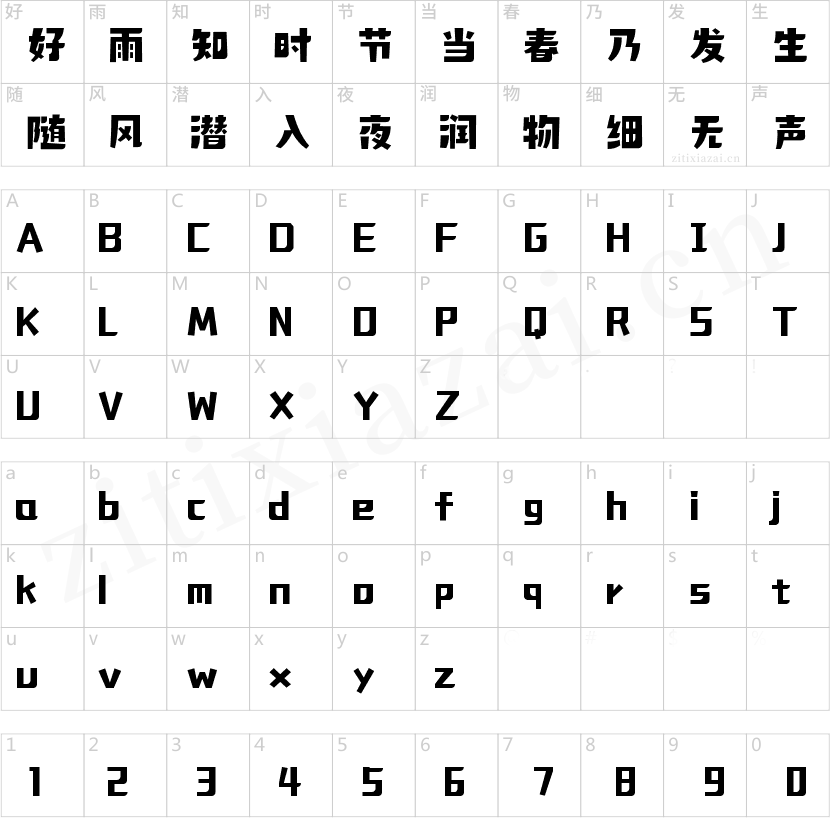
字魂轻松体
字魂轻松体,这款字体结构工整、笔画清晰,兼顾美观与易读性,适用于标题、正文、海报、包装、LOGO 等多种场景。字形优雅稳定,风格百搭耐看,适配日常排版与创意设计,让文字呈现更舒适、更具质感。字魂轻松体一笔一画,皆是细节,以均衡的比例、流畅的线条打造舒适视觉体验,字形端正大气,风格简约现代。无论是商业设计、品牌宣传还是日常排版,都能轻松驾驭,让文字更有格调与力量。字魂轻松体字体下载。
字魂字体字魂轻松体字体是由字魂创意字库设计并生产的一款可商用的字体,被收录于字魂先锋系列。该字体支持GB-2312标准,包含6763个中文、字母、符号和数字,字体类型偏向卡通可爱,具有活泼、动漫、可爱的风格,在市面上广泛用于视频综艺、活动促销、排版阅读等场景。